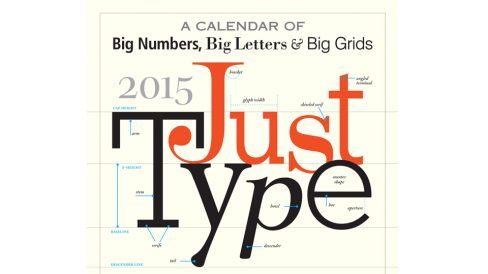
“Just Type”, um calendário que celebra a tipografia
A cada mês, uma fonte diferente, com detalhes sobre história, designers e diagramação
Criado pela Workman Publishing, o calendário Just Type 2015 foi feito para quem é aficionado por tipografia. Cada um dos meses homenageia uma fonte famosa diferente: fevereiro destaca a Matrix, primeira fonte criada em um Mac; abril é o mês da Caslon, que foi usada na impressão oficial da Declaração de Independência dos EUA; e por aí vai.
Entre as 12 fontes destacadas para a edição de 2015 estão Akzidenz Grotesk, Matrix, Rockwell, Caslon, Script, Copperlate Gothic, Century, Gill Sans, Dispatch, Bodoni, Bauhaus e Classical Engraved, com direito a explicações que detalham altura-x, arcos, bojos, aberturas, entre outras características tipográficas.